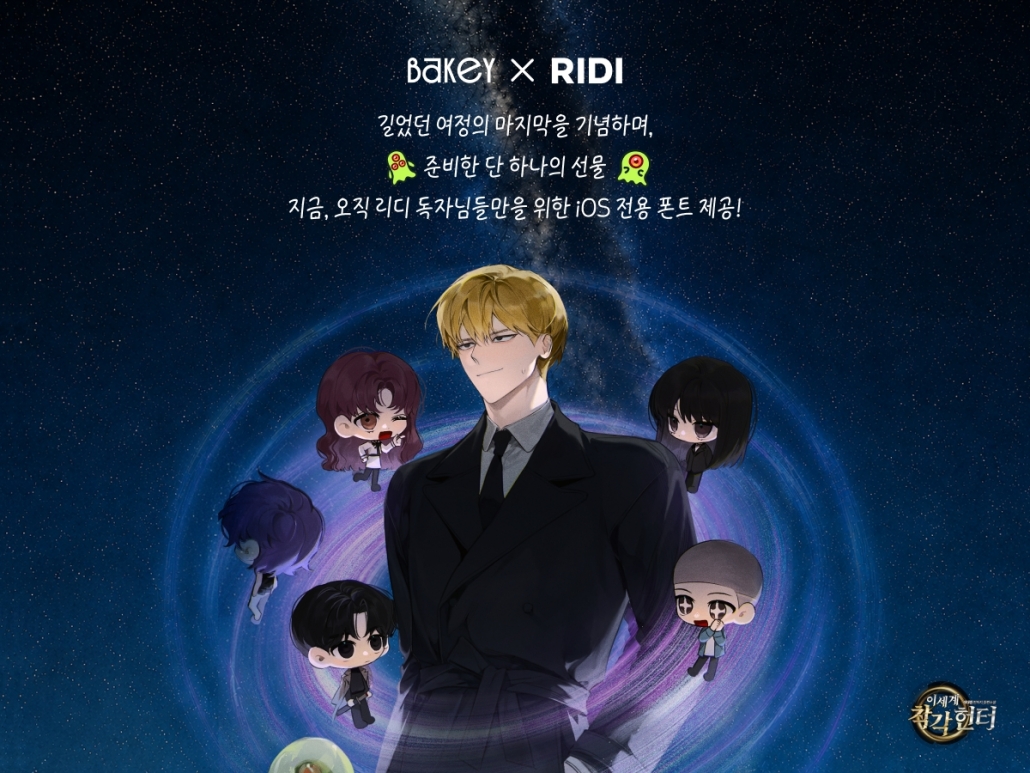
- 업계 최초 웹소설 IP 기반 모바일 폰트 ‘Iam 이세계착각헌터’ 공개
- 콘텐츠 제작 도구였던 폰트 IP 비즈니스로 진화, 테마·스티커 등 IP 기반 디지털 굿즈 사업화 확장 추진
AI 콘텐츠 플랫폼 기업 산돌(대표 윤영호)이 콘텐츠 플랫폼 기업 리디(대표 배기식)와 협업해, 인기 웹소설 ‘이세계 착각 헌터’ IP를 활용한 모바일 폰트’를 출시했다고 밝혔다.
이번 협업은 산돌이 운영하는 모바일 폰트 플랫폼 베이키의 IP 콜라보 카테고리를 웹툰에 이어 웹소설 영역으로 확장한 업계 최초 사례다. 산돌은 앞서 카카오웹툰 ‘먼지덩어리 짱덕’ IP 기반 폰트를 선보인 바 있으며, 이번 리디 협업을 통해 웹소설 팬덤까지 IP 콜라보 라인업을 확대하게 됐다.
‘이세계 착각 헌터'는 리디 독점 판타지 웹소설로, 출간 후 누적 조회수 5,000만 회를 돌파했다. 2023년과 2024년 리디어워즈 판타지 부문 대상을 2년 연속 수상한 인기 작품이며, 웹툰화 된 노블코믹스도 카테고리 상위권을 유지하고 있다.
산돌은 작품 특유의 판타지 및 이세계 분위기를 모바일 폰트에 반영해 ‘Iam 이세계착각헌터’를 개발했다. 모바일 폰트가 단순한 폰트를 넘어 이용자가 좋아하는 콘텐츠 IP를 일상 속에서 경험할 수 있는 디지털 굿즈로 자리 잡고 있는 만큼, 작품의 세계관과 상징 요소를 폰트 전반에 담아 팬덤 경험을 강화했다.
특히 이번 폰트에는 타이핑 과정에서 작품 속 행성, 외계인 등의 요소가 등장하는 ‘히든 딩뱃(Hidden Dingbat)’ 기능이 적용됐다. 해당 딩뱃에는 컬러 폰트 기술이 적용돼 지원 환경에서는 작품 세계관과 어울리는 색감이 그대로 구현된다. ‘Iam 이세계착각헌터’는 모바일 폰트 앱 베이키에서 유료 폰트로 판매될 예정이다.